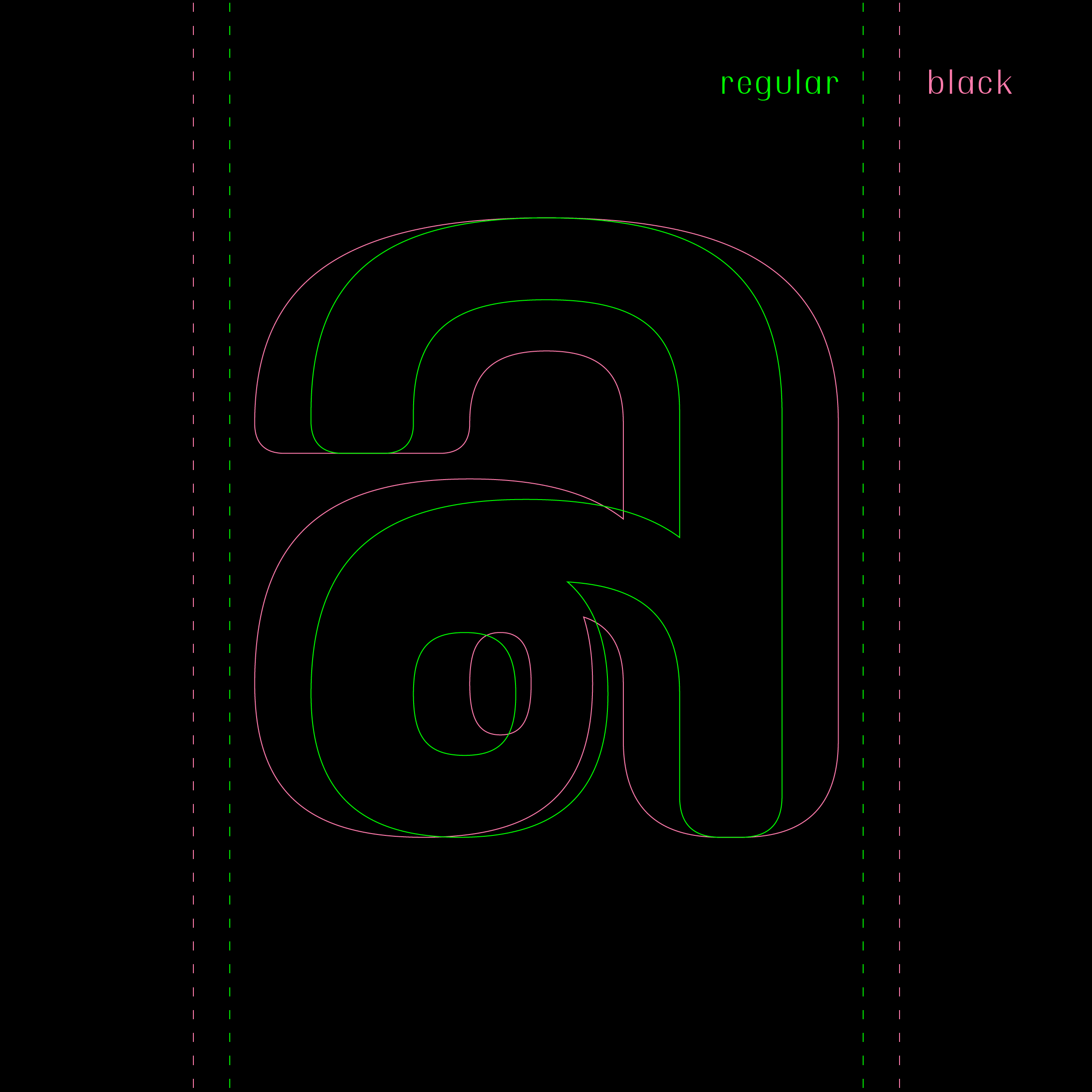
มณี นิววววววว | MANI NEUE
โปรเจกรีเมกฟอนต์เก่า >>> ฟอนต์ มณี-เมขลา
เป็นรีเมกที่รีเมกจริง ๆ คือ เอามาใช้แทนฟอนต์เก่าบ่ได้เบย  :30:
พยายาม (และหวังไว้ว่า) จะหยิบฟอนต์เก่ามาทำใหม่เรื่อย ๆ
พางานเก่า ๆ ข้ามมามาตรฐานใหม่
ซึ่งเหนื่อยกว่าทำงานใหม่อีก
หลัก ๆ คือ ชุดความคิดมันเปลี่ยนไปแล้ว
หลุดจากโจทย์นิดเดียว คือกลิ่นเดิม ๆ หายทันที
ยังงามเช่นเคย..   :12:  ชอบความ multi-master
ฟอนต์นี้น่าจะมี variable version ออกมาด้วย
ถ้าทดสอบแล้วไม่มีอะไรผิดพลาดนะฮะ
อาจจะยังดูไม่ได้หวือหวอมาก
เพราะตั้งใจให้เบาสุดแค่ regular
บางกว่านั้นมันเริ่มไม่เหมาะกับดีไซน์นี้แล้ว
จากรูปจะเห็นว่า..
ฟอนต์ชุดใหม่มีสัดส่วนที่สูงและกว้างกว่าฟอนต์มณี (เดิม) มากทีเดียว
(ในรูปคือการพิมพ์ที่ขนาด font size เท่ากัน ; 800 pt)
:12: สนใจไอเดียนี้มากครับ ถึงเวลาไม่ต้องง้อสระวรรณยุกต์บนล่างแล้ว :30:
นอกจากสัดส่วนของตัวอักษรในฟอนต์ที่เปลี่ยนไปแล้ว
ผลต่อเนื่องจากการปรับขนาดนั้น
ทำให้ระยะระหว่างบรรทัดดูลงตัวมากขึ้นด้วย
จากรูปจะเห็นว่า..
ฟอนต์ชุดใหม่ (เหมือนจะ) มีระยะบรรทัดน้อยกว่า
เมื่อเทียบกับฟอนต์มณี (เดิม)
[หมายเหตุ]
ในรูปเป็นการพิมพ์ที่ขนาด font size เท่ากัน ; 100 pt
และตั้งค่า leading เป็น auto เหมือนกัน ; 120 pt
พิมพ์เคาะบรรทัดลงมาเหมือนกัน
ชื่อฟอนต์ : มณี นิว | MANI NEUE
มณี นิว | MANI NEUE
REMAKE PROJECT จากฟอนต์สุดฮิต ฟอนต์ "มณี-เมขลา"
พัฒนาขึ้นใหม่ อัพเดต และอัพเกรดความสามารถแบบก้าวกระโดด
ยังคงความน่ารัก ใช้งานง่าย เป็นกันเอง เหมือนเดิม
เพิ่มเติมด้วยการขยายขอบเขตการใช้งานออกไป
รองรับการใช้งานได้หลากหลายภาษา
ไม่ว่าจะเป็นภาษาไทย ภาษาอังกฤษ
รวมทั้งภาษาภาคพื้นยุโรปอีกมากมาย
เพิ่มความพิเศษด้วย OpenType Features ต่าง ๆ
ไม่ว่าจะเป็นการจัดการสระ / วรรณยุกต์ไทย ด้วย Anchor Marking,
Ligatures, การทำ Kerning เพื่อความสวยงาม
ชุดฟอนต์ "มณี นิว"
ประกอบด้วยฟอนต์ 6 น้ำหนัก 12 ฟอนต์
• MANI NEUE Regular / Medium / Semi Bold / Bold / Extra Bold / Black + Italic